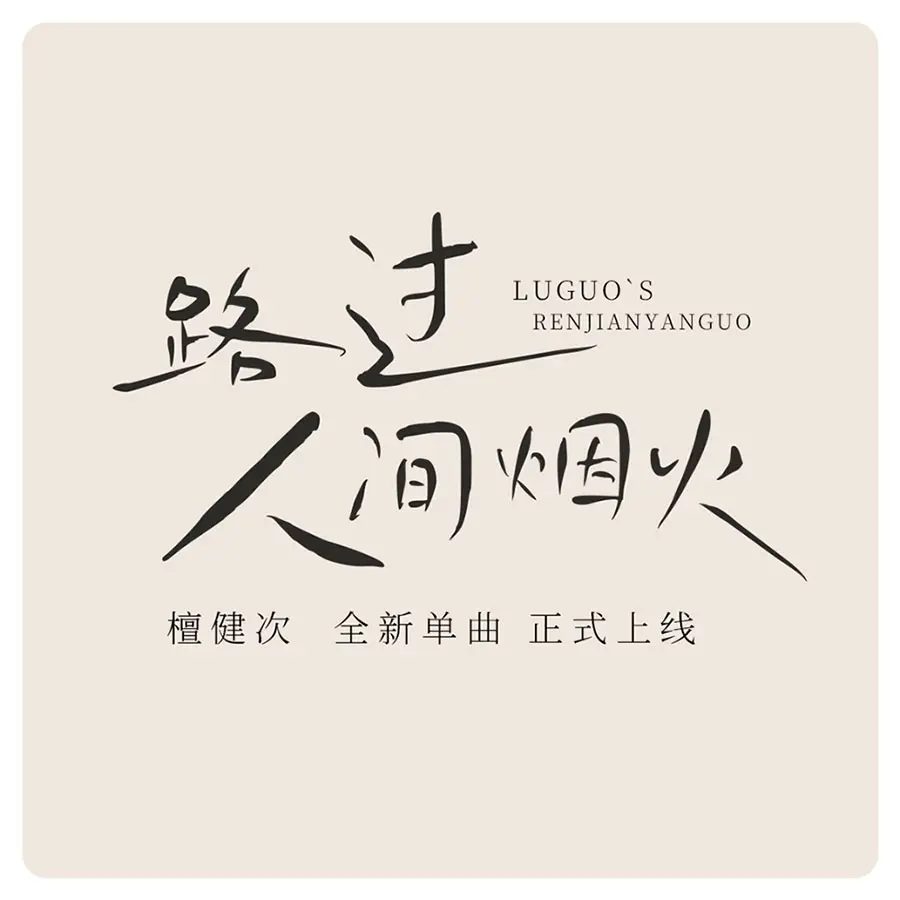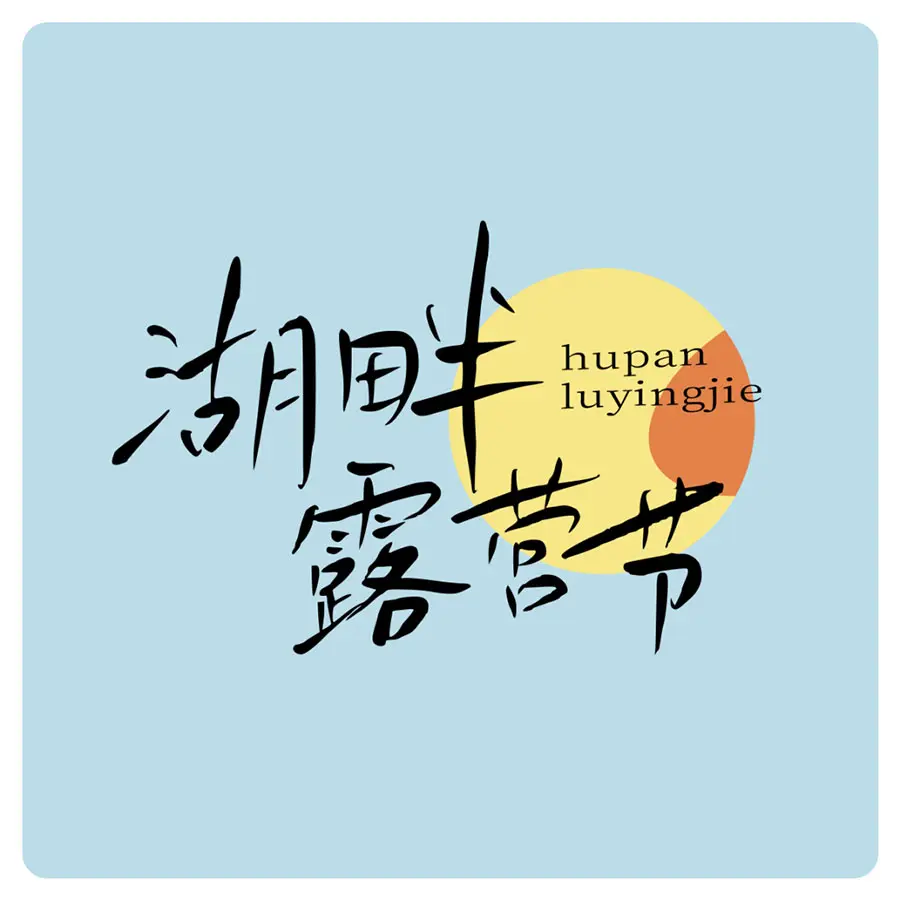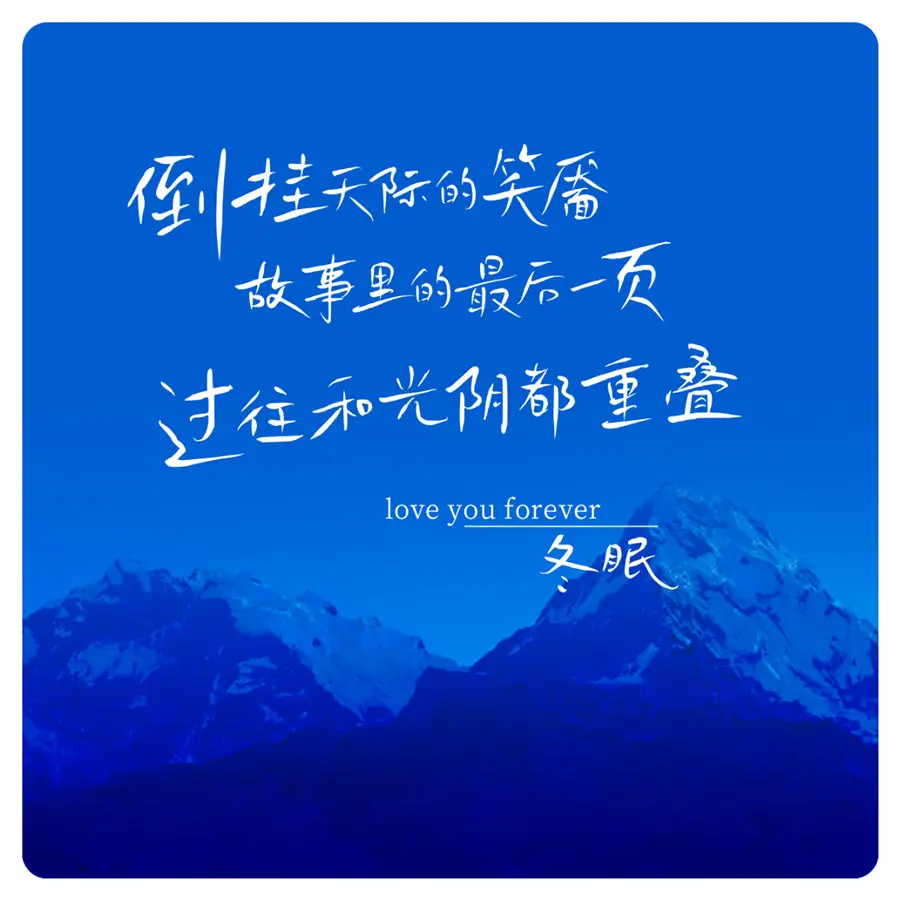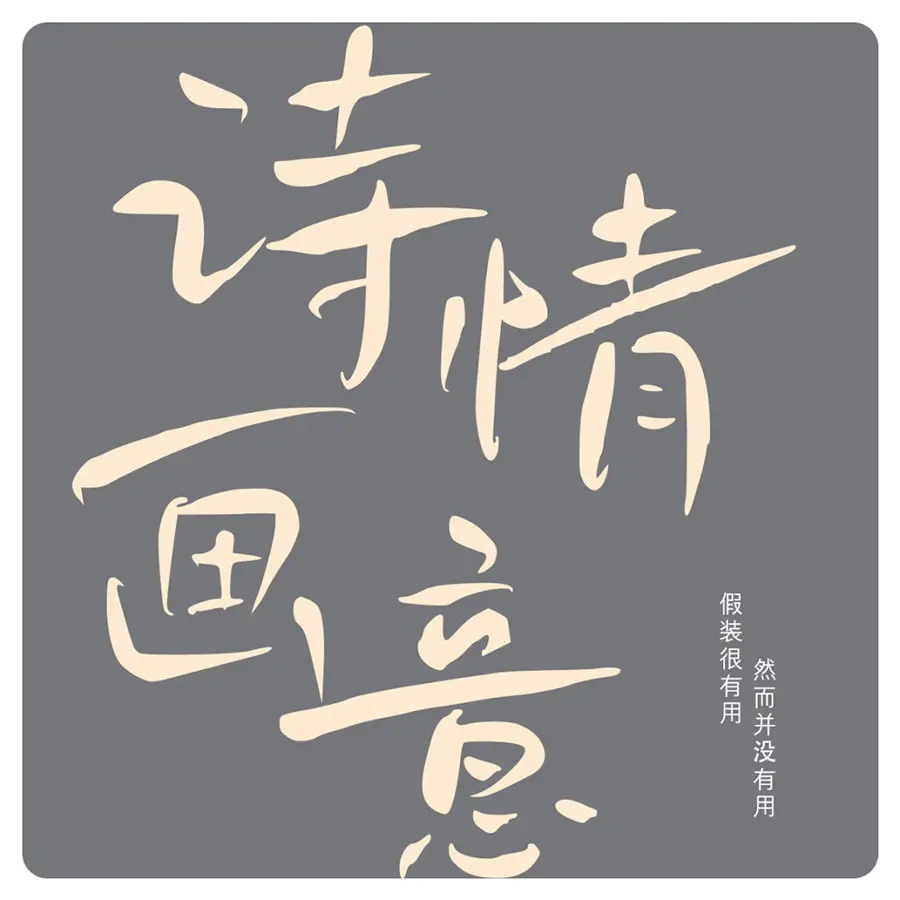
鴻雷拙書簡體預覽
鴻雷拙書簡體介紹
關於這套被我從回收站撈起來的字體簡單說兩句,這套字體寫於2021年6月份,命名為《鴻雷拙書簡體》,拙的本意就是拙略,“醜”的意思,因為寫完後才發現是真的醜,放在文件夾裡一年半了,前幾天整理文件的時候沒有任何猶豫直接被我刪了。然而前幾天有個客戶發了幾張圖給我,問我海報上面的字體會寫嗎。於是我想到剛被我刪掉不久的一套字體,我撿回來,敲上幾個字發給他,意外的是居然通過了。
突然發現字體本身也許跟人一樣,無論好壞美醜,都有人喜歡,畢竟每個人審美不同,沒辦法做出一款人人都喜歡的字體,字體的多樣性本來就是為了適應多樣性的應用場景。
從回收站撿回來後簡單的P了幾張圖看看效果,感覺也還不錯,就當提前完成今年的一個flag吧,2023完成個人的第三套免費字體。前兩套分別是《鴻雷板書簡體》發佈於2020年4月,以及《鴻雷行書簡體》發佈於2022年8月,今天2023年2月這裡正式發佈個人第三套手寫字體《鴻雷拙書簡體》。